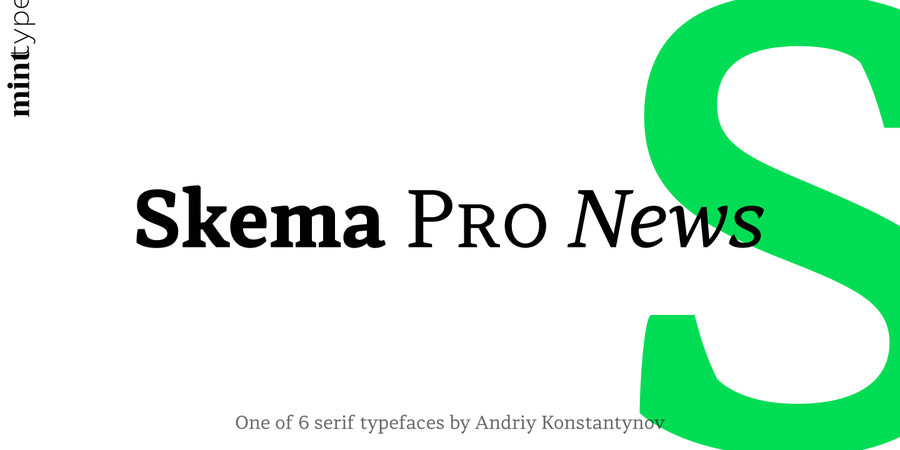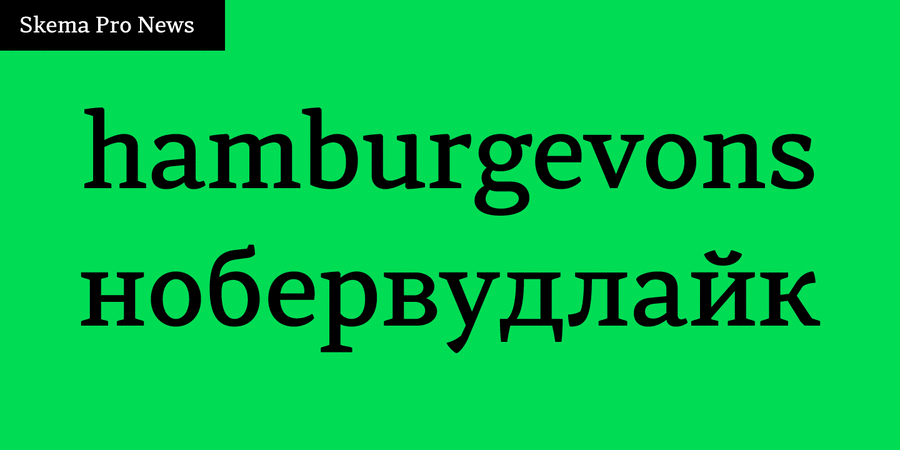
Skema Pro News – слабоконтрастна гарнітура з великою висотою рядкових та вертикальною віссю контрасту. Призначена для використання у газетах та екранних текстах.
Skema Pro – система з 6 антикв, кожна з яких має свій характер і призначення. Разом вони формують величезну супергарнітуру з 84 накреслень для будь-яких можливих завдань.
Сімейство Skema Pro розробив і випустив Андрій Константинов у студії Mint Type у 2017 році.